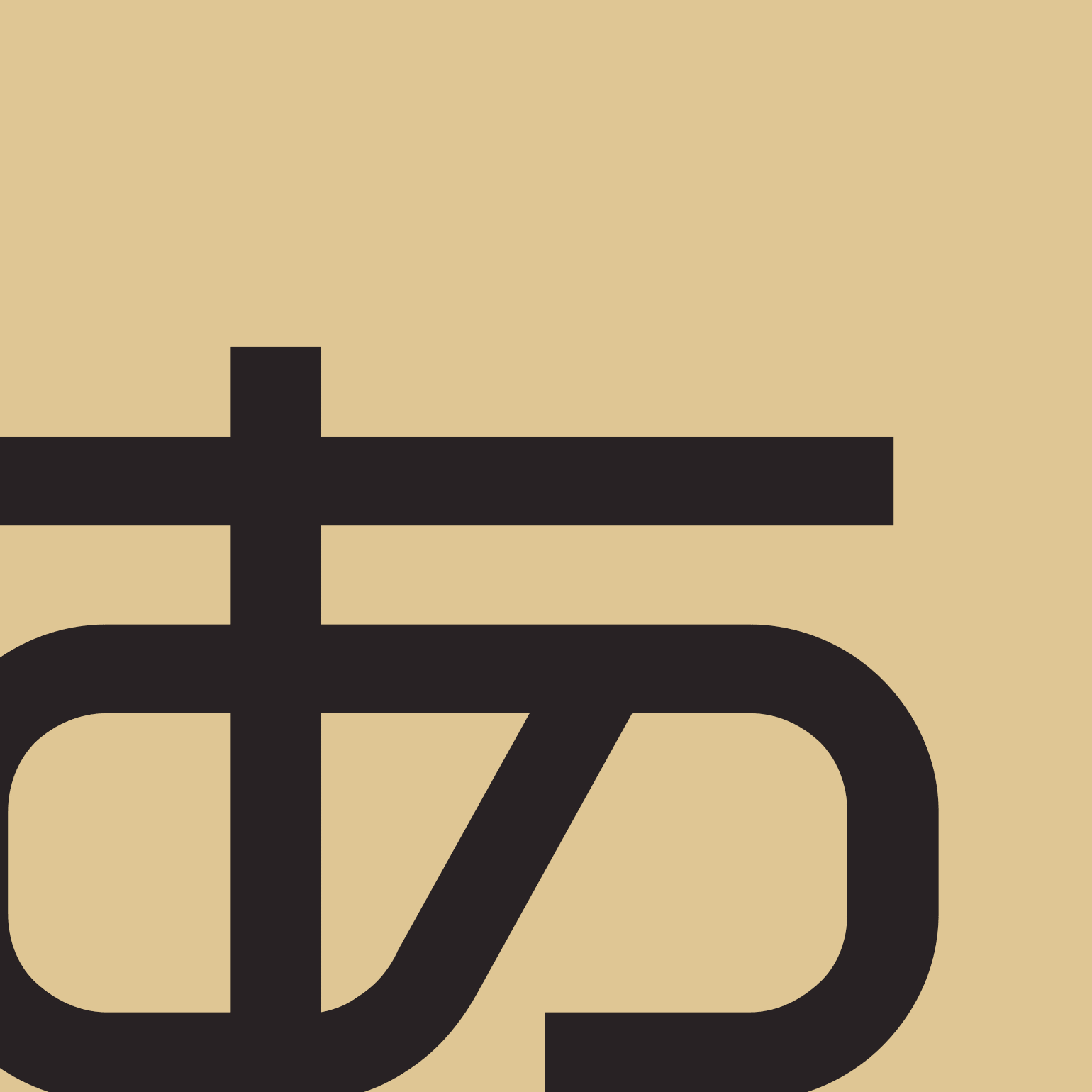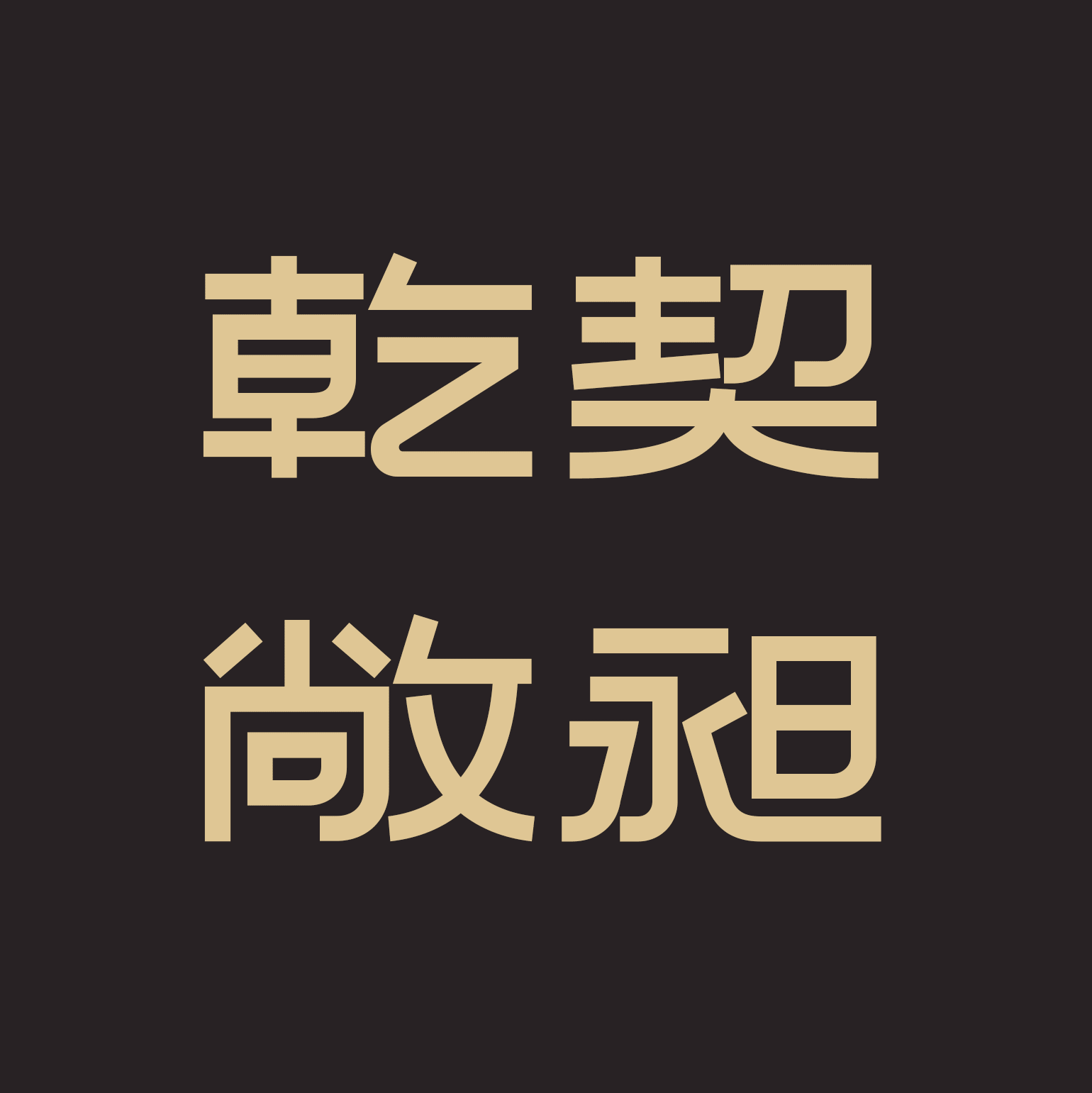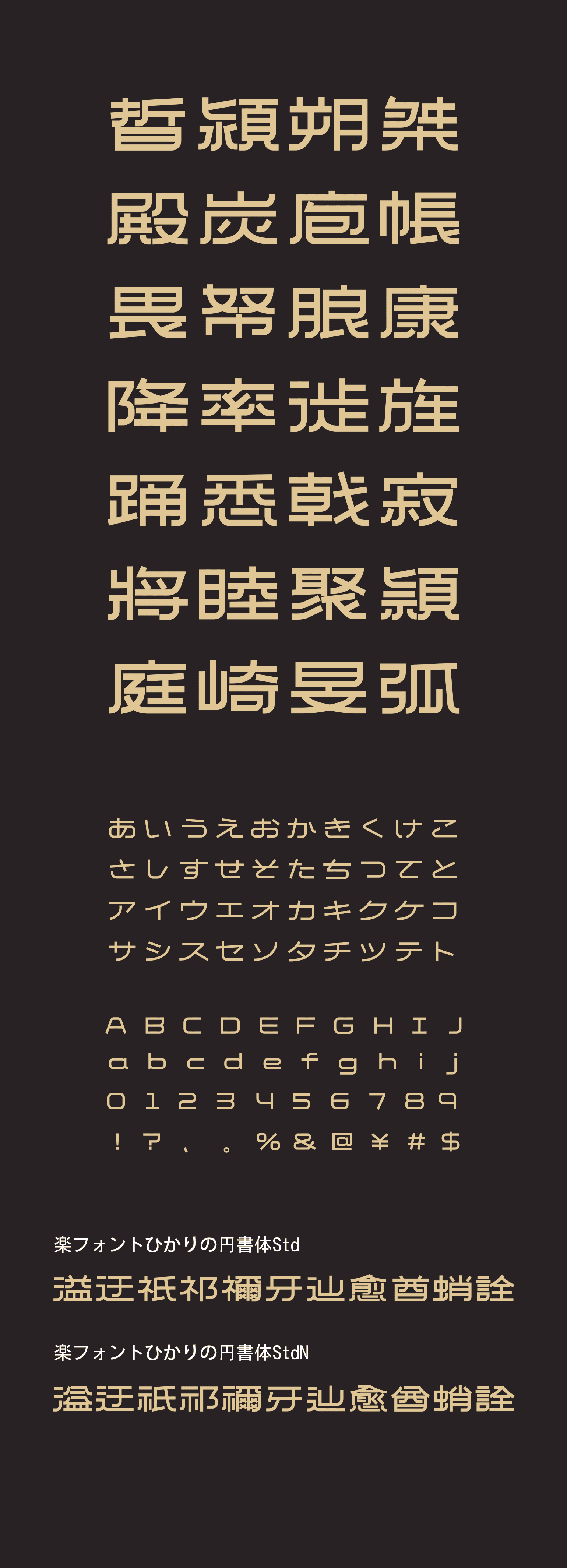
ひかりの円書体(ひかりのえんしょたい)
このフォントは、柔らかな丸みと整った幾何構造によ
り、やさしさと見やすさを両立した現代的な表情を持
ちます。なめらかな筆画が読みやすさを高め、落ち着
いた印象を生み出します。UI 表示やブランドツー
ル、教育・生活分野など、温かさと機能性を求める幅
広いデザインに最適です。